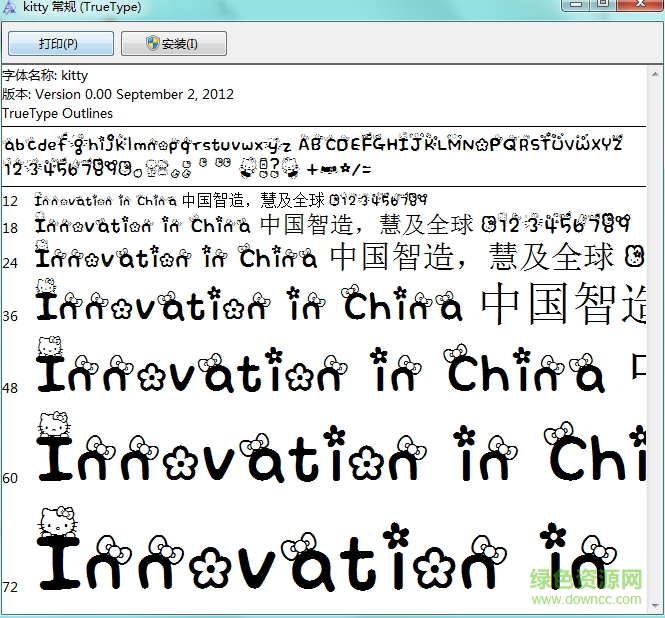
hellokitty花朵字體是一款有著可愛花朵和蝴蝶結點綴的碎花字體,給你撲面而來的滿滿的少女心體驗,讓你的文字更加生動,喜歡的朋友就來綠色資源網體驗吧!
hellokitty碎花字體是hellokitty字體的甜蜜升級版,在原始字體的基礎上增加了漂亮的花朵點綴,讓文字變得更加生動有畫面感,給孩子們帶來十分舒適的視覺體驗!
hellokitty碎花中文字體以pop字體為原形,在字體間嵌入了卡通的HelloKitty圖案,是一款很有趣的卡通字體,可以運用在兒童內容的文字修飾上,讓你的平面設計、海報設計更加吸引孩子的目光!